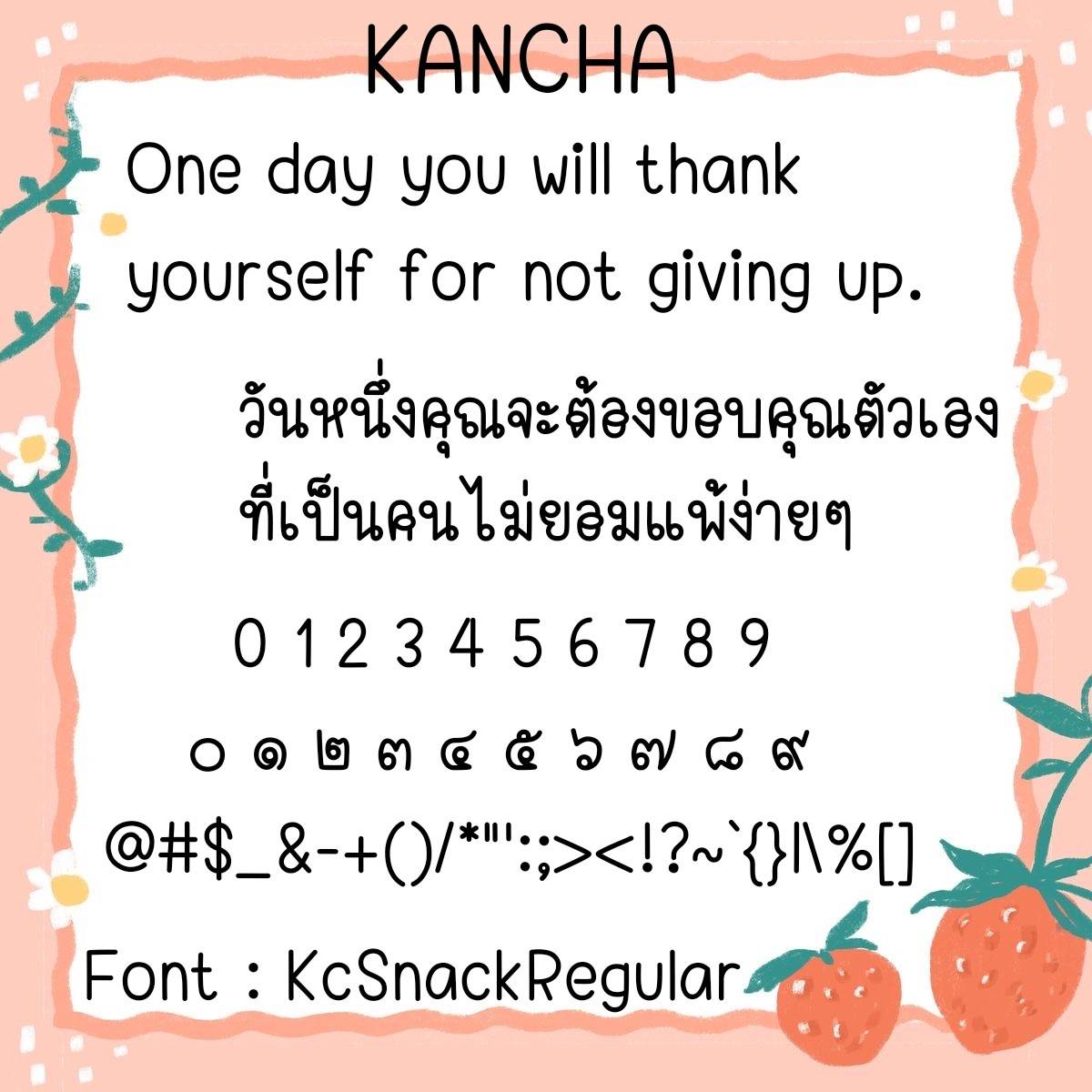
Font KcSnack
ชื่อสินค้า : Font KcSnack 💙
🔸ฟอนต์แนววัยรุ่น ตัวผอม หัวโต ดูมีสไตล์ แต่อ่านง่าย และมีอิโมจิชินจังแทนเลขไทยให้ด้วยค่ะ
🔹Teen-style font, skinny body, big head, stylish but easy to read, and has Shinchan emojis instead of Thai numbers.🥰💙